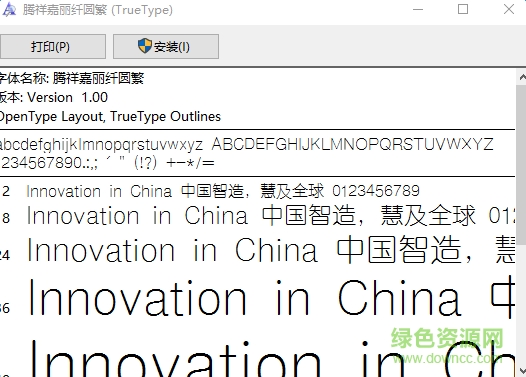
騰祥嘉麗纖圓繁體字體是一款很不錯(cuò)的電腦字體,這款字體不僅寫出來的字很好看,而且實(shí)用性也很強(qiáng),可以用于很多方面,喜歡這款字體的朋友就來綠色資源網(wǎng)下載吧。
騰祥嘉麗纖圓繁體字體是真的很不錯(cuò),寫出來的字效果很好,用于書本印刷、廣告設(shè)計(jì)等方面都是可以的,有需要的朋友可以來綠色資源網(wǎng)下載。